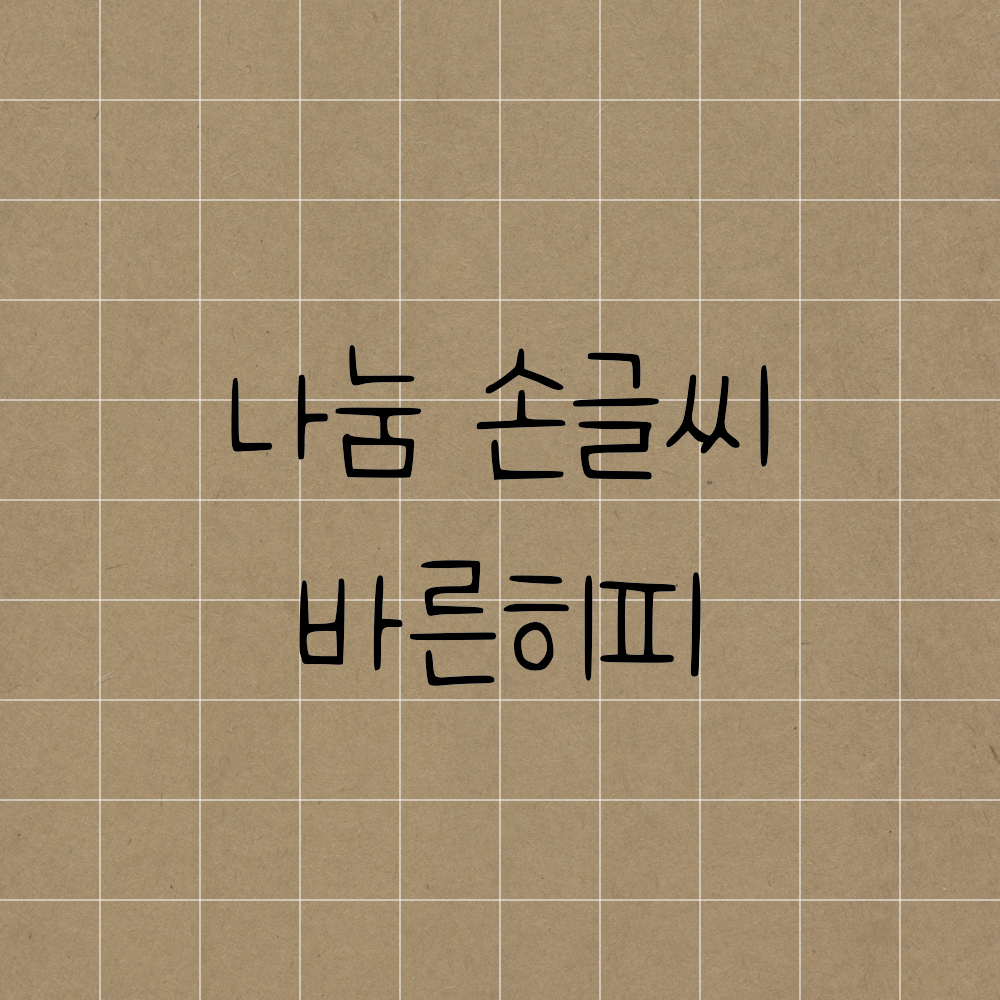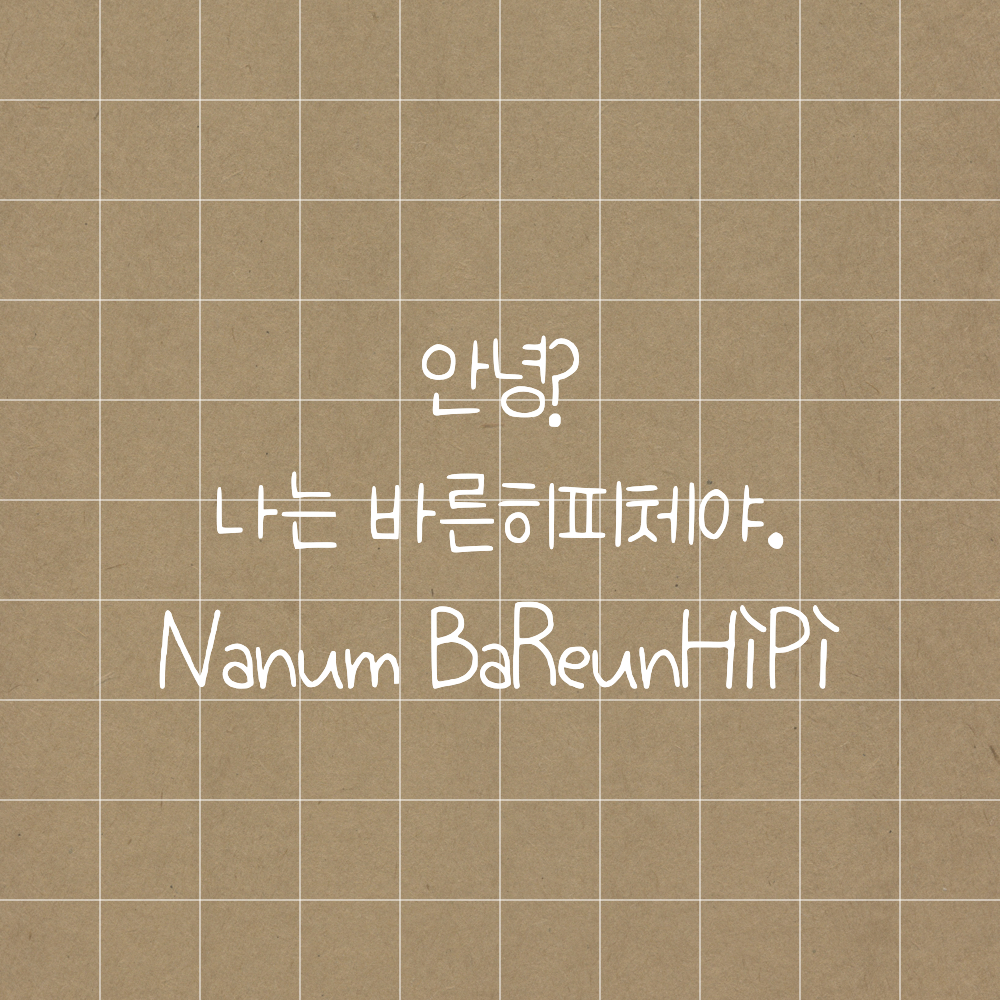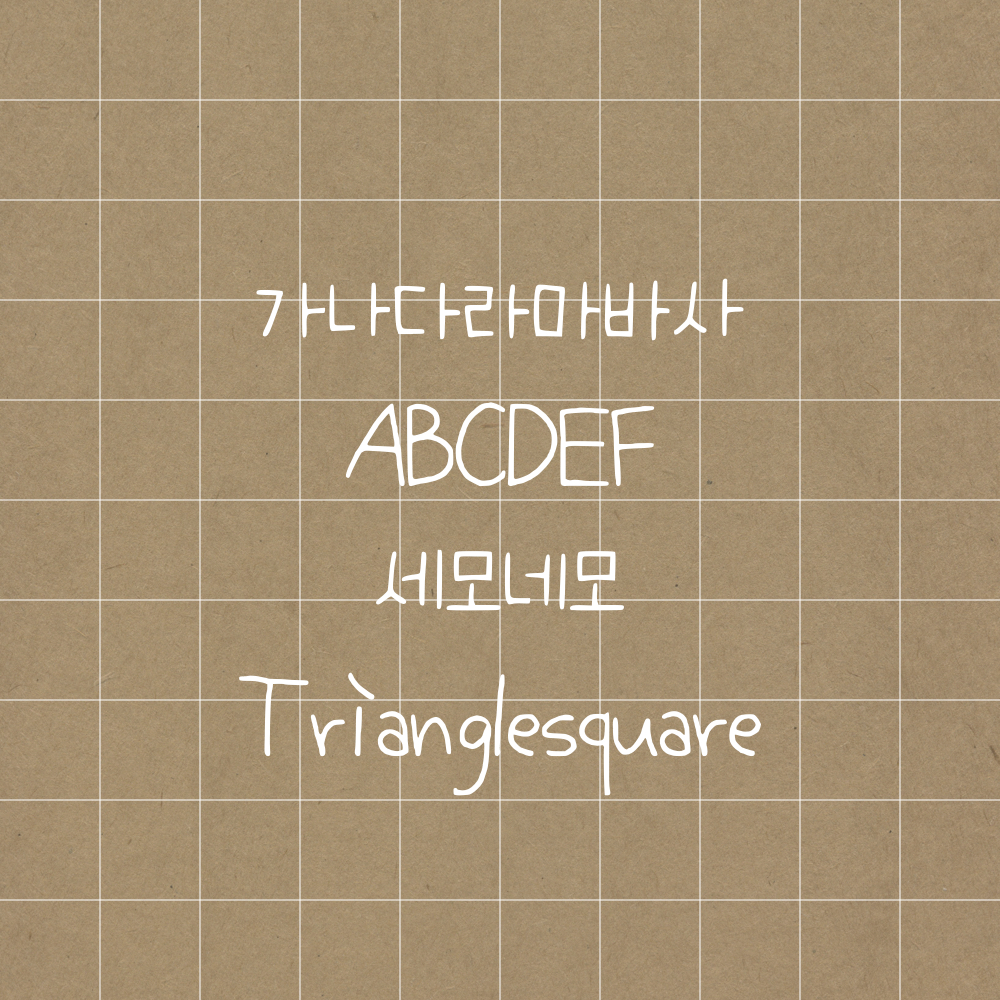
오늘의 폰트는 바른 히피체입니다💛
예쁜 손글씨체로 유명하며 네이버 블로거라면 모를 수 없는 폰트죠.
한국어와 영어를 모두 지원합니다. 그럼 예시를 한 번 살펴볼까요?
블로거 생활을 하면서 가장 많이 사용한 폰트를 소개하니 기분이 좋네요.
예쁜 글씨체인 만큼 널리 널리 퍼졌으면 하는 바람입니다.